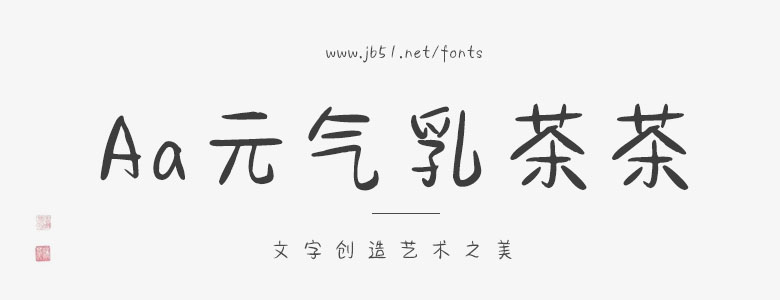
Aa元?dú)馊椴?/strong>是一款賞心悅目的藝術(shù)字體,字體線條粗細(xì)適中,筆畫隨性,結(jié)構(gòu)肆意灑脫,具有很好的視覺感,能夠應(yīng)用于文本裝潢、信息展示、網(wǎng)頁設(shè)計(jì)、篆刻制模、數(shù)據(jù)制作、裝潢設(shè)計(jì)、計(jì)算藝術(shù)設(shè)計(jì)、視覺設(shè)計(jì)、字帖等一切合法應(yīng)用場景,歡迎大家前來下載使用。
Aa元?dú)馊椴?/h3>